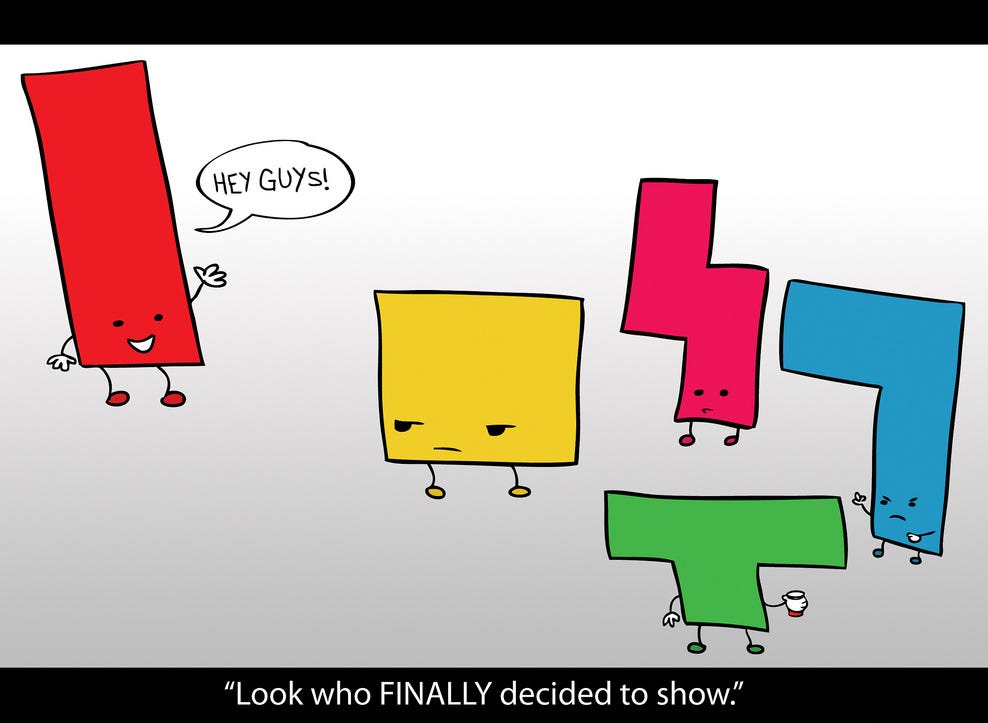
Share this postCaracteres com espaçoOlha só quem finalmente chegouCopy linkFacebookEmailNotesMoreOlha só quem finalmente chegouHeloisa LupinacciAug 10, 2010Share this postCaracteres com espaçoOlha só quem finalmente chegouCopy linkFacebookEmailNotesMoreSharePorque os altões magrinhos são sempre os mais cobiçados.